卡通字体大全,6 款免费+6 款付费商用卡通字体分享
卡通字体可以将生动活泼、圆润可爱等信息融入到文字设计中,让我们的信息传递变得更加有趣和富有感染力,能够瞬间拉近我们与读者的距离,唤起内心深处的童真与快乐。如果你正在寻找一种能让你的设计脱颖而出、充满个性和趣味的字体,那么卡通字体绝对是你不容错过的选择!本文就给大家分享一些卡通字体,包含5 款免费+5 款付费商用卡通字体。
卡通字体是一种什么字体
卡通字体就是指那些设计风格上模仿卡通形象、动漫风格,或者具有儿童绘本、涂鸦手绘等特点的字体。它们通常具有以下几个显著的特征,圆润饱满的笔画、不规则的形态、夸张的造型、手绘感强、色彩搭配多样。
卡通字体旨在营造一种轻松、活泼、有趣、富有亲和力的氛围,它能让文字不再冰冷。我经常在做一些娱乐、二次元的设计时,使用卡通字体,本文就给大家介绍一些我常用的卡通字体。
6 款免费的卡通字体推荐
优设字由棒棒体
优设字由棒棒体是由知名设计平台优设(UISDC)与字体设计师共同打造的一款创意个性字体。它以其独特的“棒棒糖”式笔画结构和活泼可爱的风格而闻名,旨在为设计作品注入童趣和活力,是设计师常用的免费卡通字体之一。
优设字由棒棒体的笔画整体饱满圆润,末端常有小圆点装饰,形似可爱的棒棒糖,非常可爱,我自己在设计时非常喜欢使用这款字体。
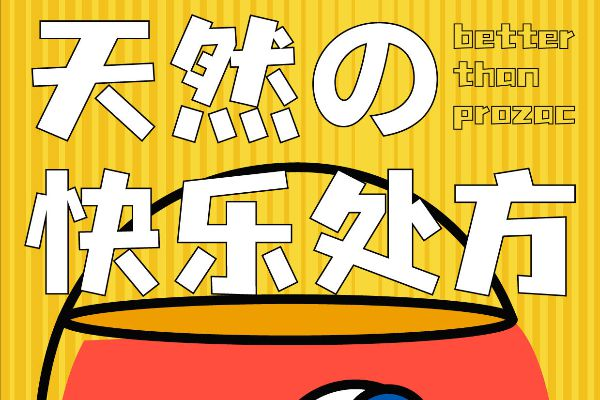
沐瑶软笔手写体
沐瑶软笔手写体是一款由沐瑶字体工作室设计开发的,具有浓郁手写风格的艺术字体。它力求还原真实软笔书写时的自然流畅感,字形娟秀,笔触细腻,充满人文气息,在需要一些手写卡通字体的场景,非常适合这款字体。
沐瑶软笔手写体非常适合用于品牌VI、文化宣传、标题字、文艺海报、影视字幕等常见,可以很好的传达柔和、艺术、传统、人文情感。对于追求手写字体、书法字体、文艺清新风格字体、雅致标题字体的设计师来说,是一款极佳的选择。
站酷快乐体
站酷快乐体是由站酷(ZCOOL)联合多位设计师共同开发的一款免费卡通字体。站酷快乐体为设计师提供一款充满活力、时尚感和亲和力的中文字体,旨在传递积极向上的“快乐”情绪,在广大设计师群体中非常受欢迎。
站酷快乐体的笔画边缘处理圆润,整体饱满,给人一种轻松愉悦的感觉,字形结构方正中带圆,重心稳定,易于阅读,同时不失活泼感。作为一款免费可商用的字体,极大地降低了设计师的使用成本,提升了普及度。
点字浅夏体
点字浅夏体是一款由点字库推出的,以“浅夏”为主题的清新风格字体。点字浅夏体笔画灵动,字形秀丽,充满诗意,是一款极具文艺气质的字体。
点字浅夏体非常适合用于文艺作品、清新风格海报、文创产品、时尚美妆、等需要营造浪漫、清新、诗意的场景。
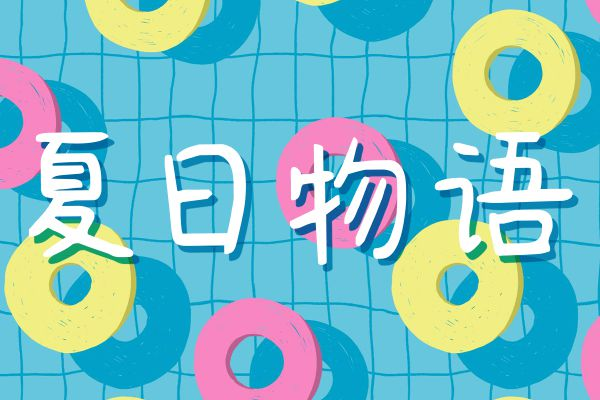
Camar
Camar是一款现代感的无衬线英文字体,以其简洁、清晰的设计风格而受到青睐。如果想寻找一个卡通的英文字体,大家可以试试 Camar 字体。
Camar 笔画多采用直线和完美的圆弧,结构严谨,具有几何美感和秩序感。Camar 字形没有多余的装饰,线条干净利落,视觉效果清爽,现代感十足。
仓耳小丸子
仓耳小丸子是仓耳字库推出的一款充满童趣和可爱风格的字体。它的设计灵感来源于儿童手绘的圆润笔触,旨在营造一种天真烂漫、活泼俏皮的视觉感受,是一款极具亲和力的儿童字体。
仓耳小丸子非常适合用于儿童读物、动画片、早教产品、玩具包装、童装品牌、母婴用品、主题乐园等需要展现可爱、童真、活泼、趣味性的场景。总之,一些和儿童相关的场景,都非常适配仓耳小丸子这款字体。
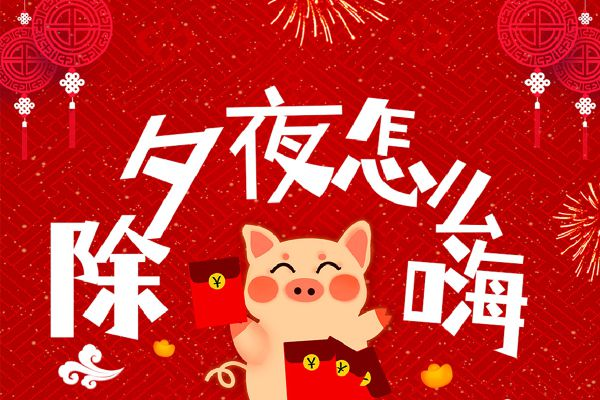
6 款付费商用的卡通字体推荐
汉仪糯米团
汉仪糯米团是汉仪字库推出的一款充满软糯、Q弹、可爱风格的卡通字体。它的设计灵感来源于糯米团子的软萌形象,笔画圆润饱满,整体给人一种温暖治愈的感觉,是一款兼具可爱与温馨的字体。
汉仪糯米团像糯米团一样富有弹性,视觉上带来柔软和亲切感。汉仪糯米团字体整体散发出一种温暖、可爱、亲切的气息,具有疗愈感和包容性。
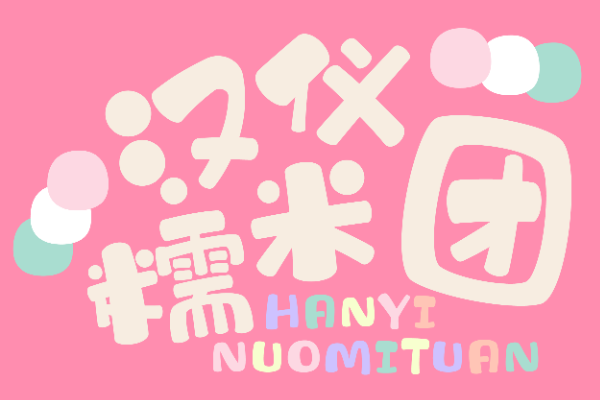
华康海报体
华康海报体是华康字库推出的一款专为海报设计而生的卡通字体。它以其粗壮、醒目的字形和强烈的视觉冲击力而著称,旨在确保在各种宣传媒介上都能清晰、有力地传达信息,是设计师常用的标题字体。
华康海报体字体笔画厚重,字形饱满,具有强大的视觉冲击力,能在第一时间抓住眼球。专为大字号标题设计,在远距离或复杂背景下依然保持极高的辨识度。
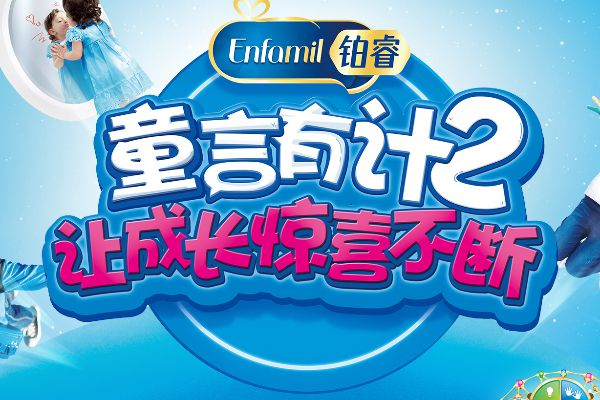
汉仪铸字童年体
汉仪铸字童年体是汉仪字库推出的一款充满童真和怀旧气息的卡通字体。汉仪铸字童年体字体笔画粗细不均,略带涂鸦感,字形结构不完全规整,充满儿童的稚拙美。
汉仪铸字童年体非常适合用于儿童教育、怀旧主题活动、文创产品等场景。我曾经在做一个趣味标题字体的时候选择的就是这款汉仪铸字童年体。
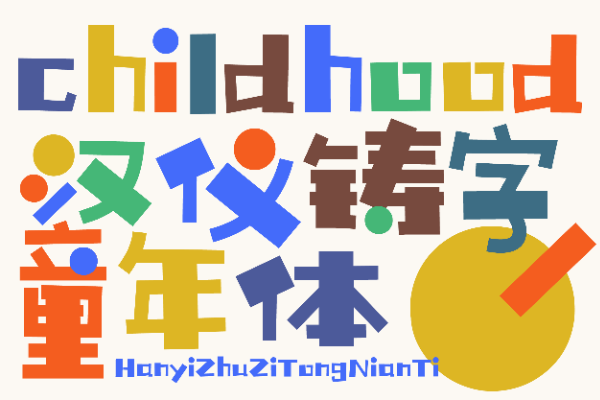
汉仪铸字木头人
汉仪铸字木头人是汉仪字库推出的一款极具个性和创意的手写风格字体。它的设计灵感可能来源于木偶或木头玩具的结构特征,笔画僵直却不失童趣,整体风格独特而富有张力,是一款艺术感和设计感兼具的字体。
汉仪铸字木头人非常适合用于个性品牌Logo、文创产品、潮流海报、独立游戏设计、潮牌服装等场景。
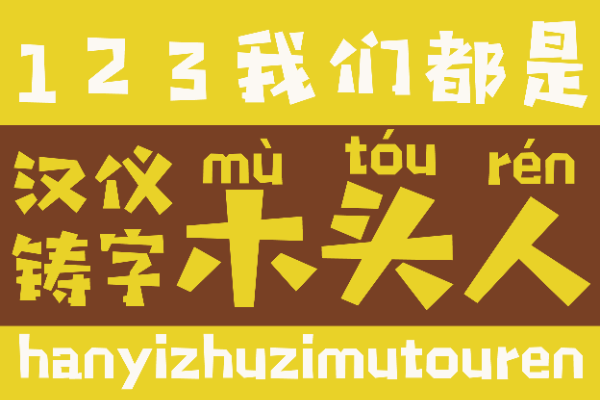
点字灵动体是由点字库推出的一款充满活力和轻盈感的卡通字体。点字灵动体笔画线条纤细,转折圆润,整体书写感流畅,给人一种轻快的感觉。
点字灵动体非常适合用于时尚杂志、美妆品牌、轻食餐饮、文创产品等场景。
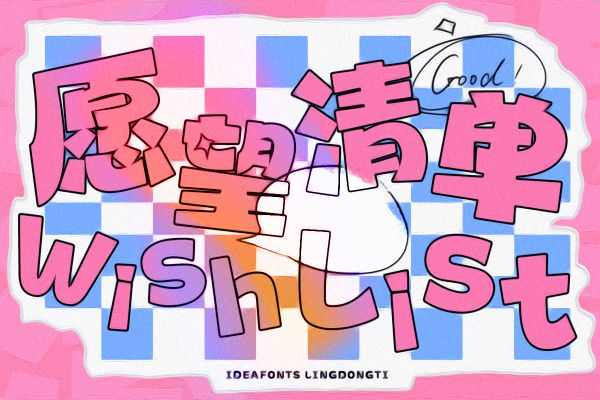
点字墩墩体是由点字库推出的一款憨厚可爱、圆润饱满的卡通字体。它的设计灵感来源于“墩墩”这一形象,直接非常具体形象的体验了这款字体的风格和特点。
点字墩墩体其独特的憨萌气质能有效营造轻松愉快的氛围,提升品牌好感度和情感连接。是寻找可爱字体、Q版字体、儿童字体、治愈系字体、温馨标题字体的优质选择。